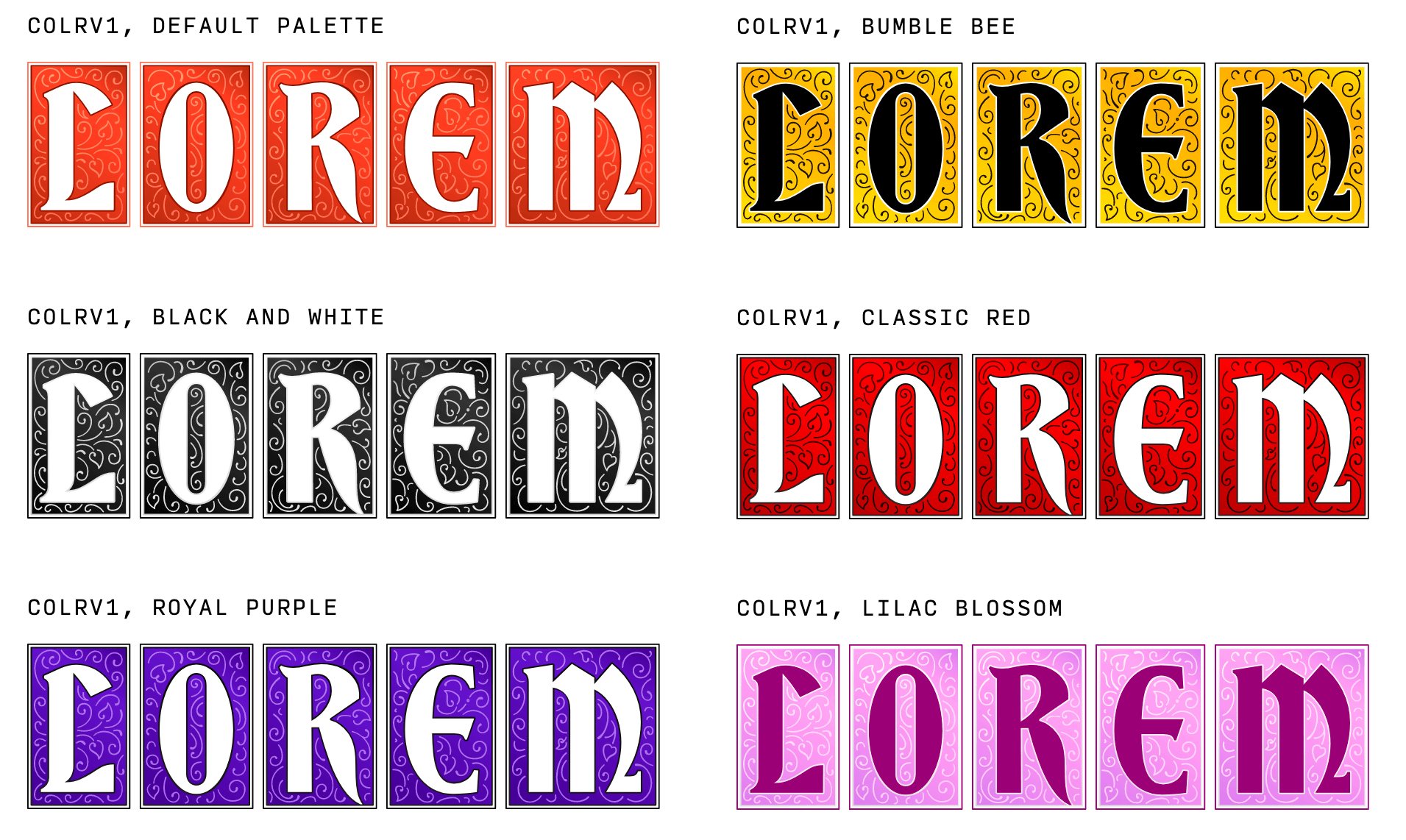
フォント
序章
ウェブフォントの黎明期から、私たちは長い道のりを歩んできました。ほんの一握りのウェブセーフフォントから、何十万ものウェブフォントというタイポグラフィの爆発的な普及につながったのです。その技術や使いやすさは、ほとんど認識できないほどです。いくつかのフォントフォーマットを使った手の込んだ「bullet-proof」フォント読み込み戦略から、単にWOFF2ファイルを含むだけというものまで。
Webフォントのこの進歩が示すもの。ウェブフォントの利用率は伸び続けています。2020年のフォントの章では、デスクトップサイト全体の82%がWebフォントを使用していました。それから2年で、使用率は約84%に増えています。モバイルでは若干数値が下がりますが、同様の伸びを表しています。
私たちは大きな進歩を遂げましたが、まだそこまでには至っていません。世界の人口の大部分はWebフォントを使用できません。なぜなら、彼らの文字システムは、(小さな)Webフォントとして提供するには大きすぎるか、複雑すぎるかのどちらかだからです。幸い、W3Cフォント・ワーキンググループ は、インクリメンタルフォントトランスファー ウェブ標準に熱心に取り組んでおり、うまくいけばこれを解決できるかもしれません。
2021年はFontsの章がありませんでしたが、今年はその分を取り戻せたらと思っています。今年は、フォントファイルの中身や、CSSでフォントがどのように使われているかを詳しく調べることで、少し違った角度から見てみました。もちろん、サービス、font-display
、リソースヒントの使い方といった「基本」にも立ち返りました。最後に、 可変フォント と カラーフォント に焦点を当てた2つの特別なセクションで、この章を締めくくります。
パフォーマンス
がデスクトップとモバイルで0%と使用されています。意外なことに、提供されるフォントの種類にはあまり変化がありません。全フォントファイルの約75%はWOFF2として、約12%はWOFFとして、残りはオクテットストリームまたはとして提供されています。 TrueType Fontと、それからランダムなMIMEタイプの一群です。これは、2020年のフォントの章の結果とかなり似ています。幸いなことに、SVGとEOTのフォント使用はほとんど完全になくなりました。
2019年、2020年に記載した通りです。WOFF2は最高の圧縮を提供し、好ましいフォーマットであるべきです。実際、宣言する時期でもあると思われます。
WOFF2だけを使い、他のことは忘れてください。
これにより、CSSとワークフローが大幅に簡素化され、またフォントのダウンロードが誤って二重になったり、不正確になったりするのを防ぐことができます。WOFF2は現在、あらゆる場所でサポートされています。ですから、よほど古いブラウザをサポートする必要がない限り、WOFF2を使ってください。そうできない場合は、古いブラウザにウェブフォントを一切提供しないことを検討してください。これは、しっかりとしたフォールバック戦略をとっていれば問題ありません。古いブラウザの訪問者は、単にあなたのフォールバックフォントを見ることができます。
ホスティング
人々はどこでフォントを入手しているのでしょうか?セルフホストか、ウェブフォントサービスを使うか?両方ですか?数字を見てみましょう。
一般的には、67%がセルフホスティングとサービスを利用しています。セルフホスティングのみを利用しているのは19%に過ぎません。キャッシュ パーティショニングの導入後、ホスティング サービスを使用することによるパフォーマンスの利点はもはやないこと、および 欧州の裁判所は、欧州に拠点を置く企業がGoogleフォント を使うことに徐々に強い疑念を持つようになっていることの理由からこの数字は今後数年間で上昇することが見込まれています。
このデータをさらにサービス別に分けることができます。驚くことではありませんが、Googleフォントはもっとも多くのウェブフォントサービスで、すべてのウェブページの65%近くが使用しています。無料に勝るものはありませんね。
次点は、フォントAwesomeというウェブサービスで、7%近くのサイトで使われているそうです。たった1つのフォントファミリーで、この結果はすごいことです。3位はAdobeフォントで、4.2%のサイトで使用されています。また、Fonts.com と Cloud.Typography は、どちらも0.2%のサイトで使用されているサービスです。
例年を振り返ってみると、今年ははじめてGoogleフォントの使用率が減少していることがわかります。これが前述のキャッシュパーティションによるものなのか、GDPRによるものなのか、それともまったく別のものなのか、何とも言えません。減少幅はわずかなので、この傾向が来年も続くかどうかが注目されます。
一方、フォントAwesomeとAdobeフォントの両サービスは、ここ数年で大きく成長しました。フォントAwesomeサービスの利用率は2019年から2022年にかけて86%成長し、Adobeフォントの利用率は同期間に24%成長した。
なお、サービスデータは、2020年および2019年のフォントの章と比較して、測定方法が異なります。それらの章では、サービスへのリクエスト数を調べたのに対し、2022年のデータでは、サービスを利用しているページを調べています。したがって、2022年のデータは、サイトに読み込まれたフォントの数に影響されないため、より正確なものとなっています。たとえば、2020年の章で指摘したGoogle Fontsの使用率の低下は、Google Fontsが 可変フォント に切り替えたことにより、サービスへのリクエスト数が大幅に減少したことがもっとも大きな原因でした。
ファイルサイズ
圧縮は、ダウンロードする必要のあるデータ量を減らすのに最適な方法ですが、それには限界があります。フォントのファイルサイズに影響を与えるものをよりよく理解するために、全フォントのフォントサイズの中央値を見てみましょう。
フォントサイズの中央値は約20キロバイトです。これは結構なことです。しかし、先に見たように、フォントサービスは全フォントリクエストの70%近くを占めています。GoogleフォントやAdobeフォントのようなサービスには、フォントをできるだけ最適化するためのチームがあり、フォントサイズの中央値は、これらのサービスによって大きく歪められている可能性があります。
セルフホスティングのフォントサイズを見ると、まったく違うことがわかります。フォントサイズの中央値は約2倍の約40キロバイトに達しています。これはいったいどういうことなのでしょうか。人気のあるウェブフォントのMIMEタイプのグラフをもう一度見て、ウェブフォントサービスからのリクエストをすべて削除してみると、何が起こっているのかがわかるかもしれませんね。
セルフホストフォントを使用している多くのサイトがWOFF2ではなく、いまだにWOFFを使用しています。これらのサイトのフォントが、WOFF2が導入されてから一度も更新されていないのか、あるいはWOFF2について知っている開発者が少ないのか、はっきりしません。いずれにせよ、簡単にできる最適化であり、多くのサイトが恩恵を受ける可能性があります。
しかし、サービスとセルフホスティングのフォントサイズの中央値の差は、WOFF2の使用率の低さで説明するには大きすぎる。WOFF2は優れた圧縮機能を備えていますが、圧縮だけではフォントサイズの中央値の大きな差は説明できません。ウェブフォントサービスは、セルフホストフォントでは十分に行われていない、他の種類の最適化を実行しているはずです。その答えを見つけるには、フォントの内部を見る必要があります。
OpenTypeのテーブルサイズ
典型的なフォントは、基本的に 小さなリレーショナルデータベース であり、それぞれのテーブルにはグリフの形状、グリフの関係、メタデータなどのデータが格納されています。たとえば、フォントの文字であるグリフを構成するベクターベジエ曲線を格納するテーブルがあります。また、グリフ同士を関連付けるテーブルもあり、カーニングや合字の関係(有名な リガチャ 合字のように、この2つのグリフを一緒に使うときはこのグリフと入れ替える)などが格納されています。
あるテーブルがファイルサイズ全体に与える影響を測定する合理的な方法は、そのテーブルの中央値を、そのテーブルを含むフォントの数に乗じることです。
OpenTypeテーブル | インパクト |
---|---|
glyf (ベクター形状) |
79.6% |
CFF (ベクター形状) |
4.9% |
GPOS (位置づけ関係) |
4.7% |
hmtx (水平配置量) |
2.5% |
post (メタデータ) |
2.2% |
name (名前メタデータ) |
1.4% |
cmap (文字コードとグリフを対応させる) |
1.3% |
fpgm (フォントプログラム) |
0.9% |
kern (カーニングデータ) |
0.6% |
もっとも高い影響力を持つテーブルのトップ10は、glyf
、CFF
、GPOS
、hmtx
のテーブルから始まります。これらには、すべてのグリフのアウトラインを構成するベジエ曲線(glyf
とCFF
)、OpenTypeポジショニング機能(GPOS
)、水平メトリクス(hmtx
)のデータが含まれています。これらの表はフォントのグリフ数に直接関係しているので、これは素晴らしいことです。不要なグリフを削除してフォントのグリフ数を減らせば、そのファイルサイズを劇的に減らすことができます。
何が必要、不要なのかを見極めるのは難しいところです。誤ってグリフを削除してしまったり、テキストを正しくレンダリングするために必要なOpenType機能を壊してしまったりする可能性があります。たとえば フォントツール を使って手動でサブセットする代わりに、subfont や glyphhanger などのツールを使って、サイトのコンテンツに基づいて「完璧な」サブセットを自動的に作成できます。ただし、フォントのライセンスがそのような変更を許可しているかどうかには注意してください。
興味深いのは、name
テーブルとpost
テーブルがもっとも多い10位に入っていることです。この2つのテーブルは主にデスクトップフォントには重要だが、ウェブフォントには必要ないメタデータを含んでいます。これは多くのウェブフォントが、名前テーブルのエントリ、post
テーブルのグリフ名、非Unicodeのcmap
エントリなど、影響を与えずに削除できるメタデータを含んでいることを示しています。私たちは、ファウンドリやウェブ開発者がウェブ フォントの不要なバイトをすべて削除するために使用できる、普遍的な推奨事項(または pngcrush に似たツール)をぜひ見たいと思っています。
を必ず使用してください。これらを組み合わせることで、あなたのサイトのフォント読み込みパフォーマンスにもっとも大きな影響を与えることができます。
ここ2、3年、Googleのおかげで、可変フォントが華々しく登場しました。もっともパフォーマンスが高いからという理由で使っている人が多いようですが、私たちは、このようなケースは、採用が革新をもたらすと信じています。今後、どのような楽しいタイポグラフィやクレイジーなタイポグラフィが登場するか、楽しみです。
カラーフォントについても、慎重に楽観視しています。利用がようやく増えてきたのです。技術は以前からあったのですが、カラーフォントのフォーマットに関する意見の相違や、CSSのサポートが限られていることが、採用の妨げになっています。これらがすぐに解決され、本当の意味での成長が見られるようになることを期待しています。
Webフォントの利用は、今後も増え続け、時代とともに進化していくことは間違いないでしょう。私たちは、未来がどうなるかを知りたいと思っています。Incremental Font Transferのようなテクノロジーは、より多くの文字システムにウェブ フォントを提供し、何十億もの人々がはじめてウェブ フォントを使い始めることを可能にします。それは楽しみですね。